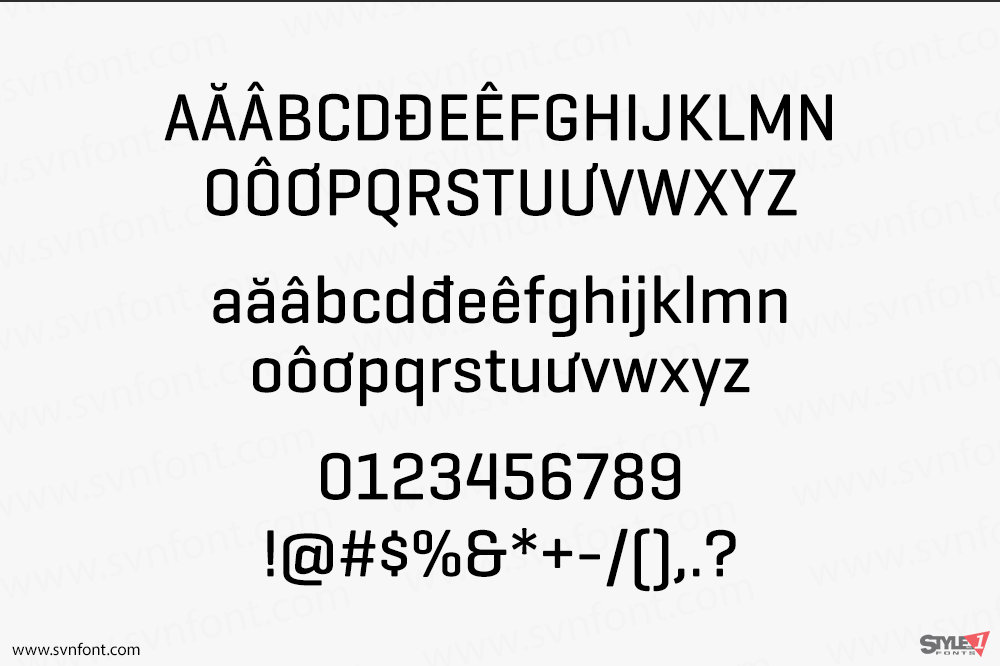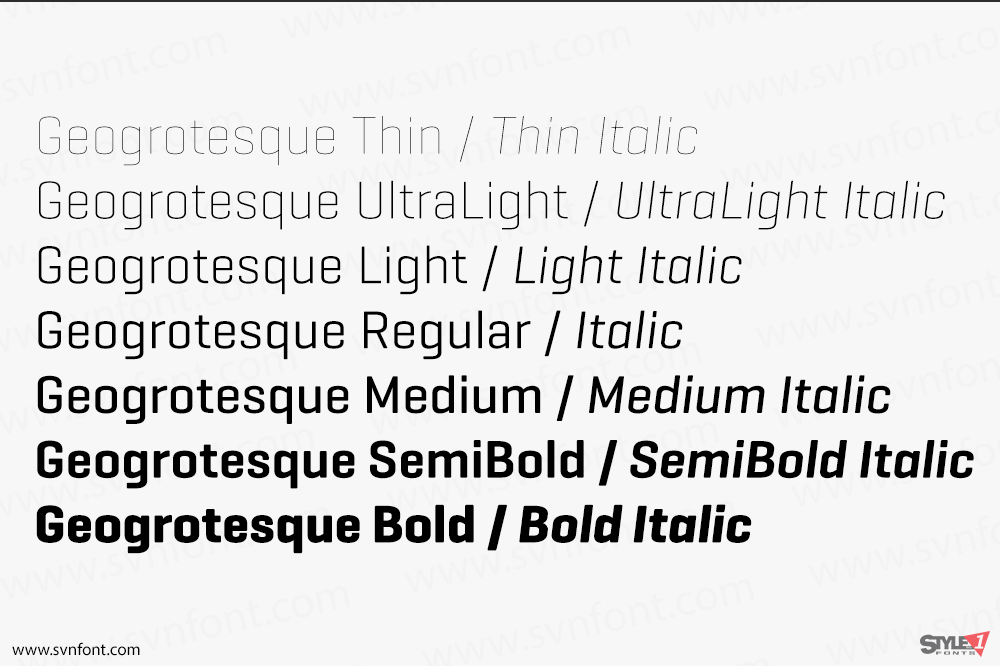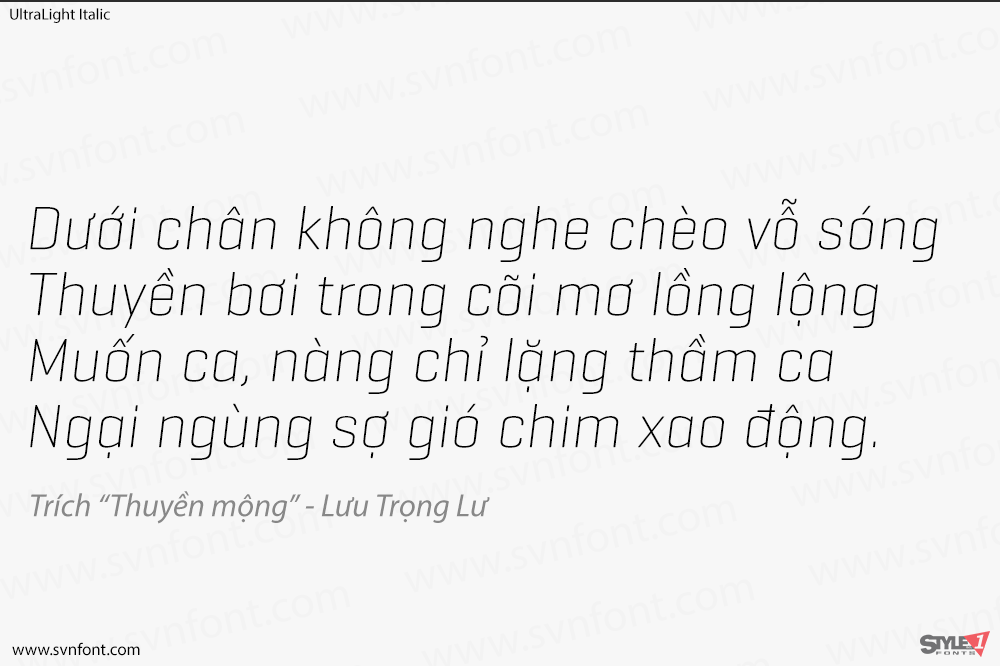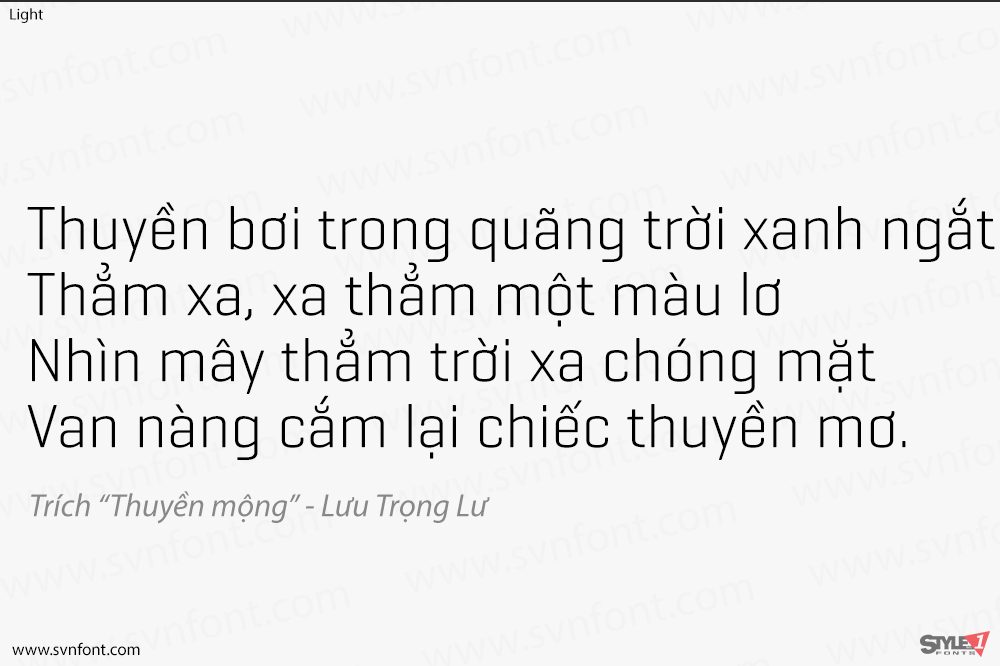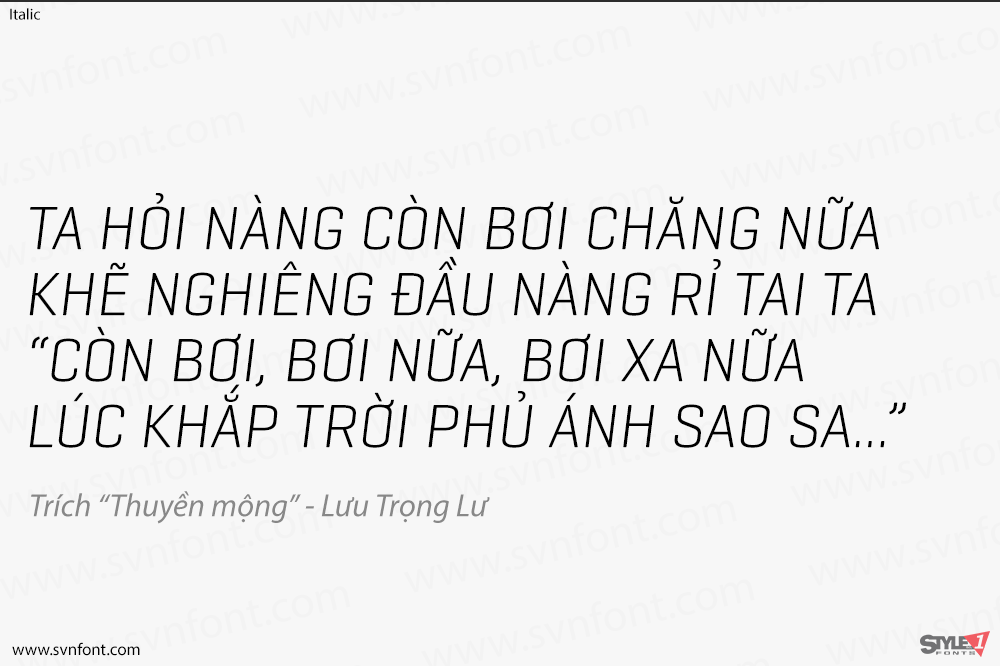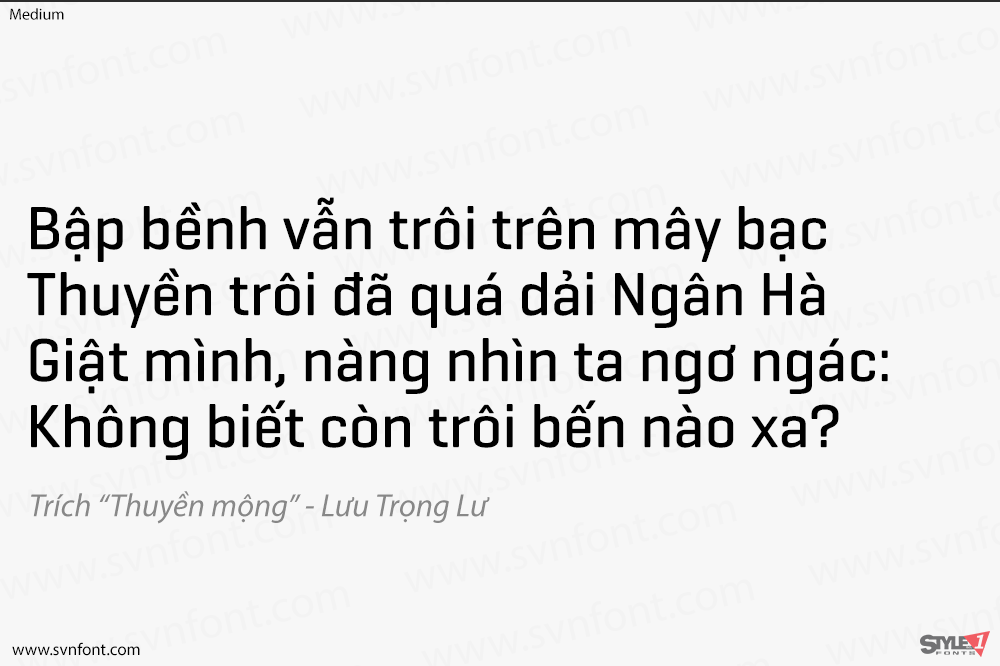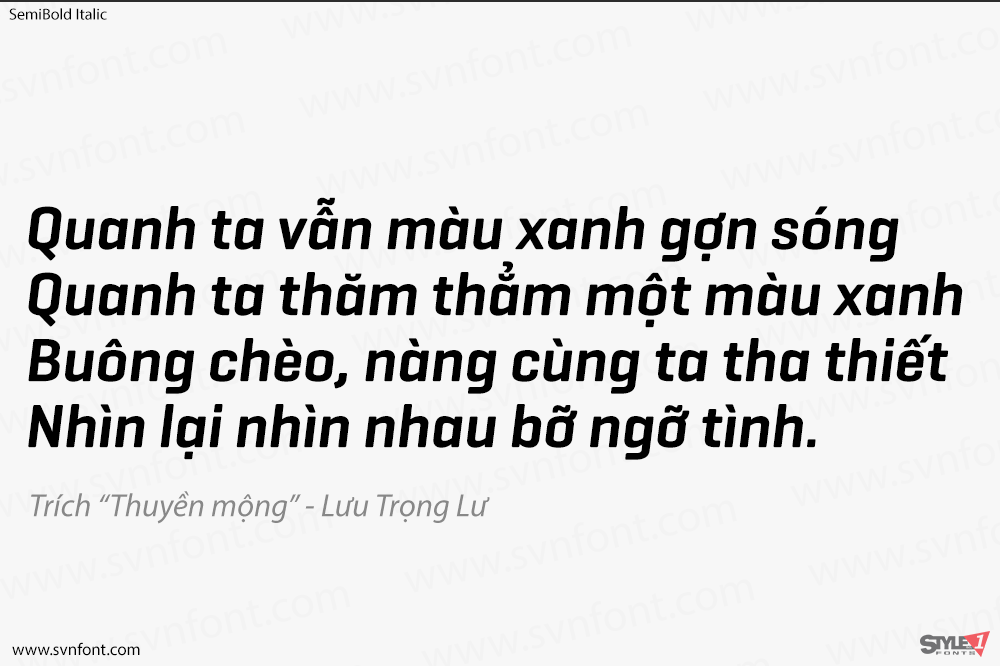
Geogrotesque là một kiểu chữ bán mô-đun với lớp hoàn thiện bo tròn tinh tế. Tất cả các ký tự đều dựa trên cùng một nguyên tắc hình thức với các điều chỉnh quang học tương ứng để điều chỉnh hệ thống thành một bảng chữ cái cho văn bản. Mặc dù họ kiểu chữ có cấu trúc hình học hoặc công nghệ, lớp hoàn thiện bo tròn mang lại cho nó một vẻ ngoài ấm áp, làm cho các kiểu chữ trở nên đẹp hơn và gần gũi hơn. Geogrotesque đã được hình thành để sử dụng làm kiểu chữ hiển thị trong các ấn phẩm hoặc văn bản có độ dài trung bình, đặc biệt là các độ đậm Thin và Ultralight được thiết kế để sử dụng ở kích thước lớn.
Nhà thiết kế: Eduardo Manso
Nhà phát hành: Emtype